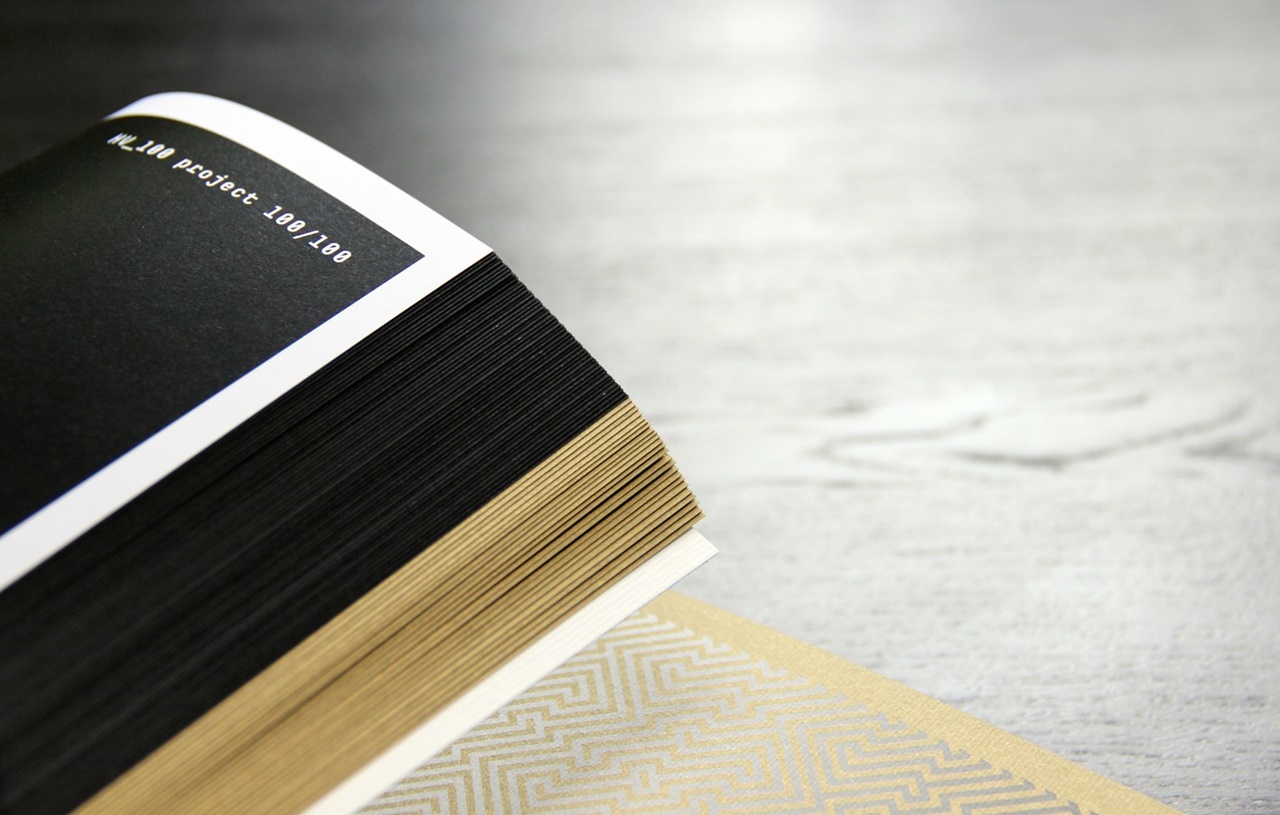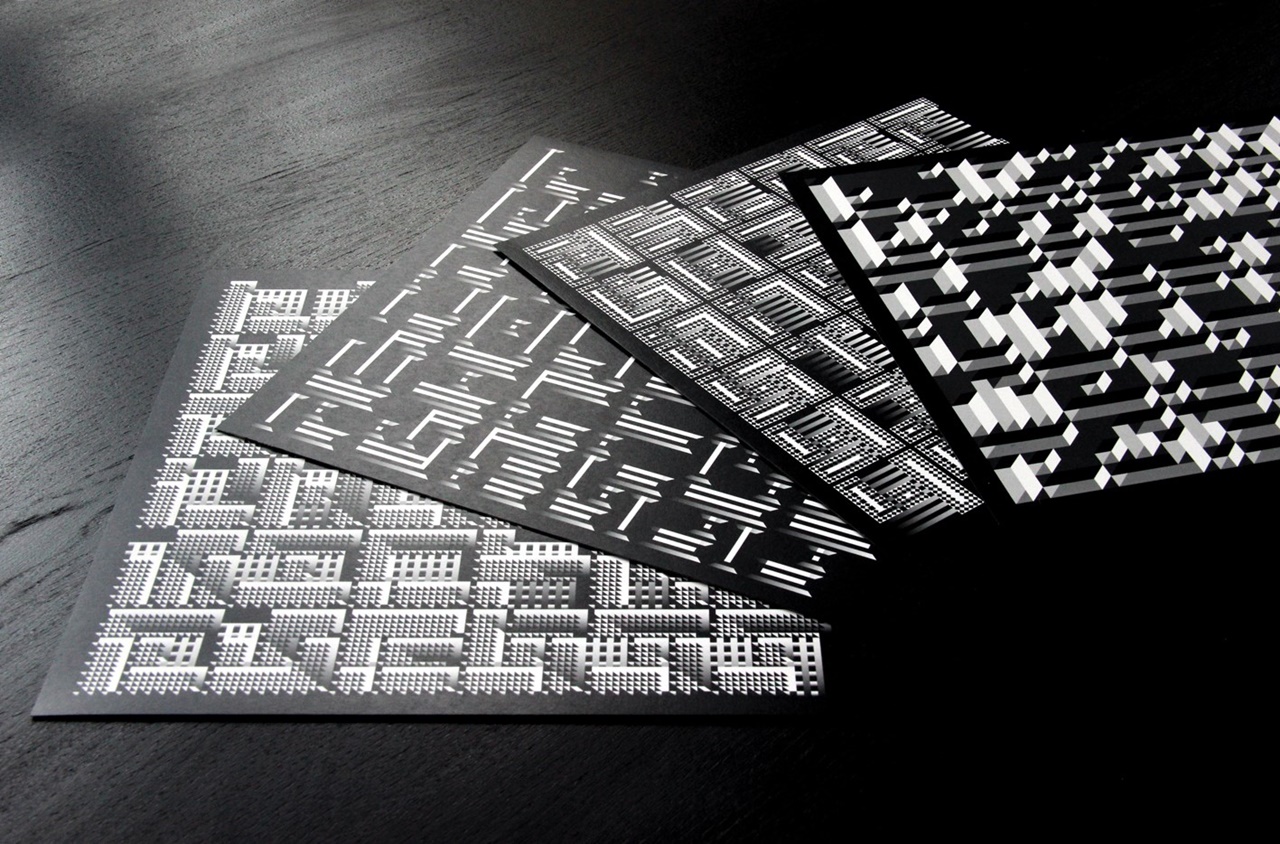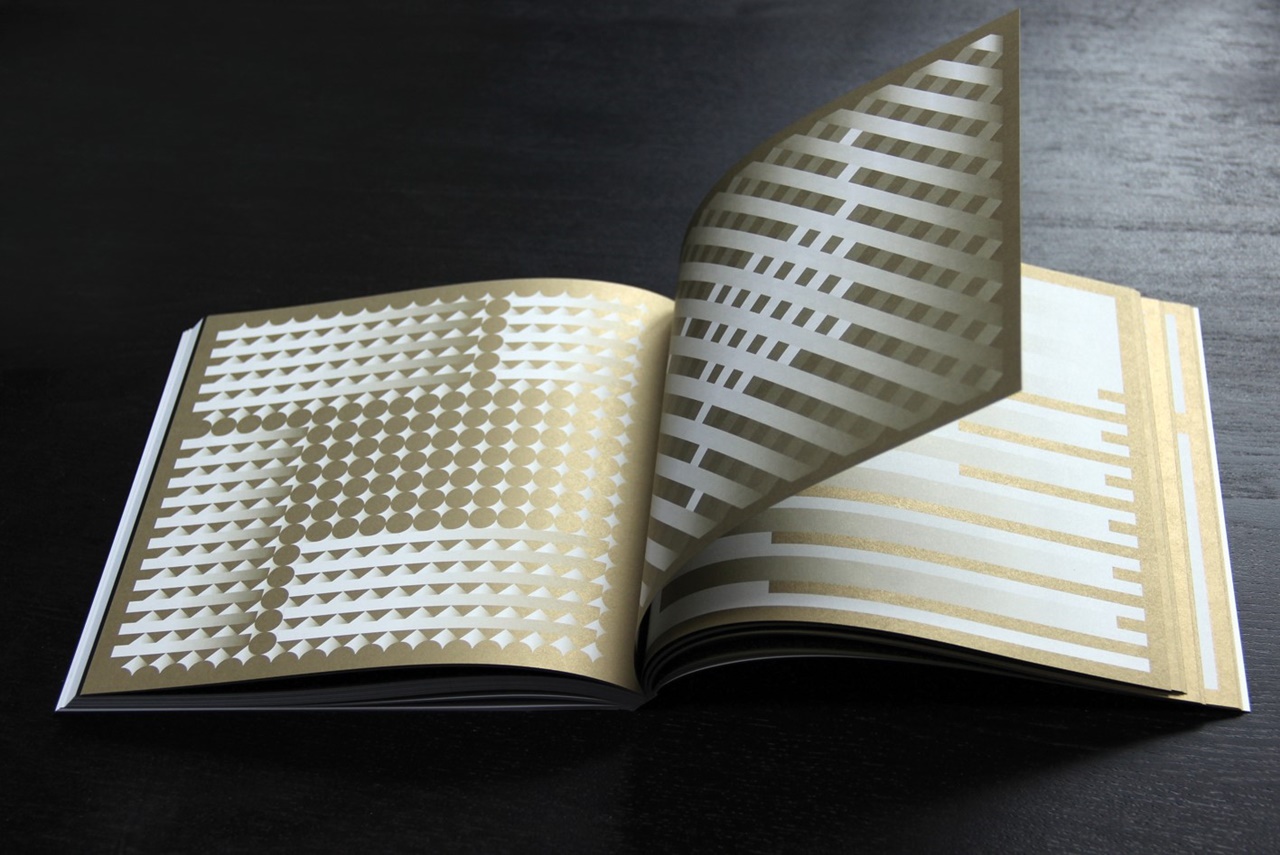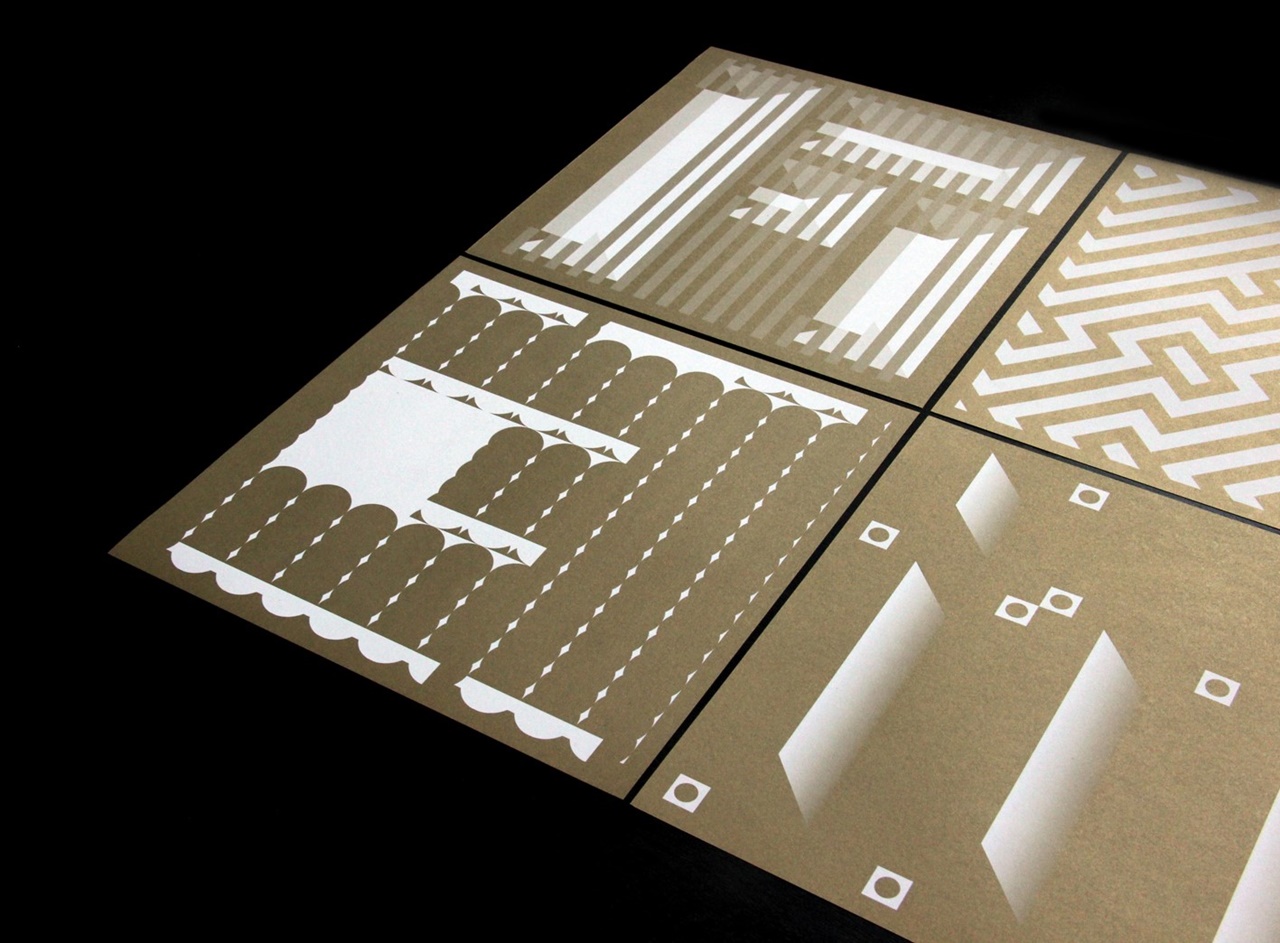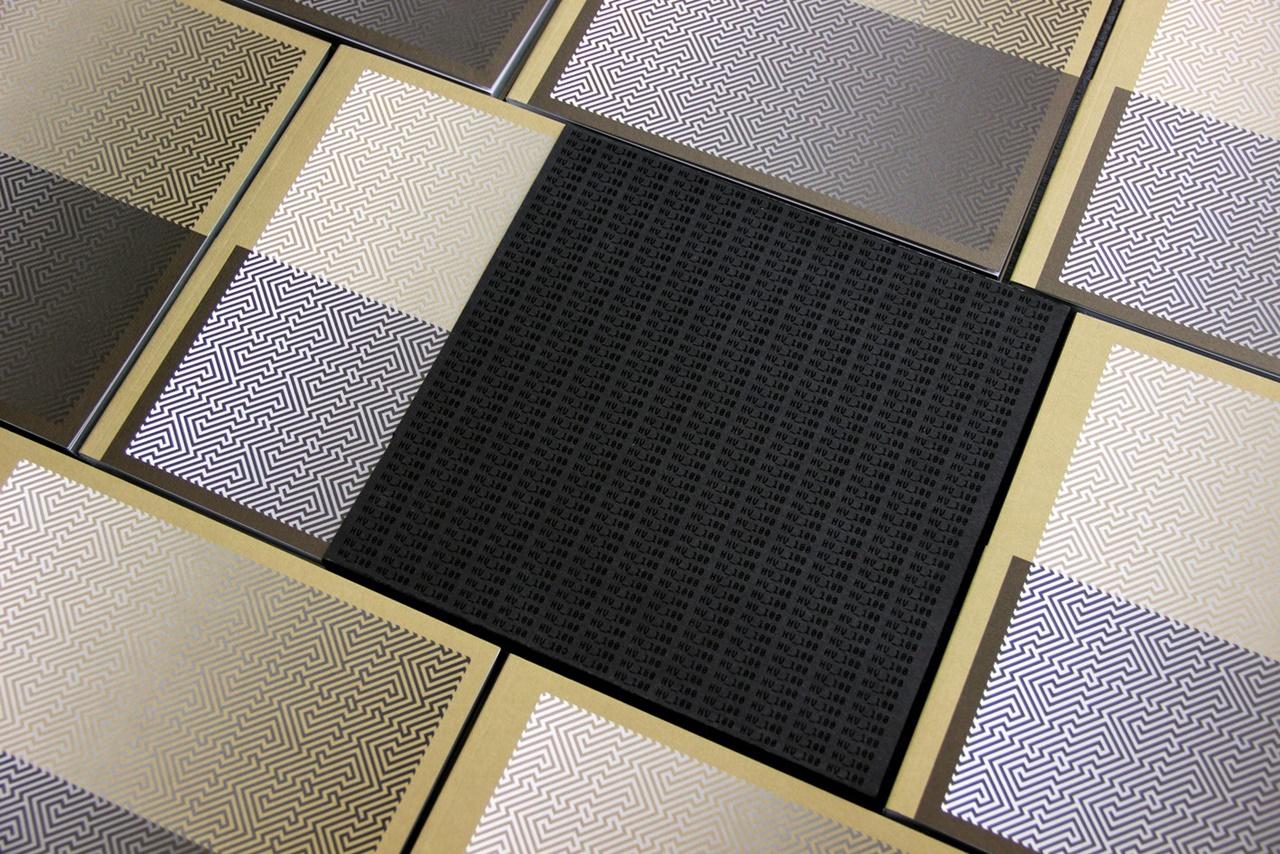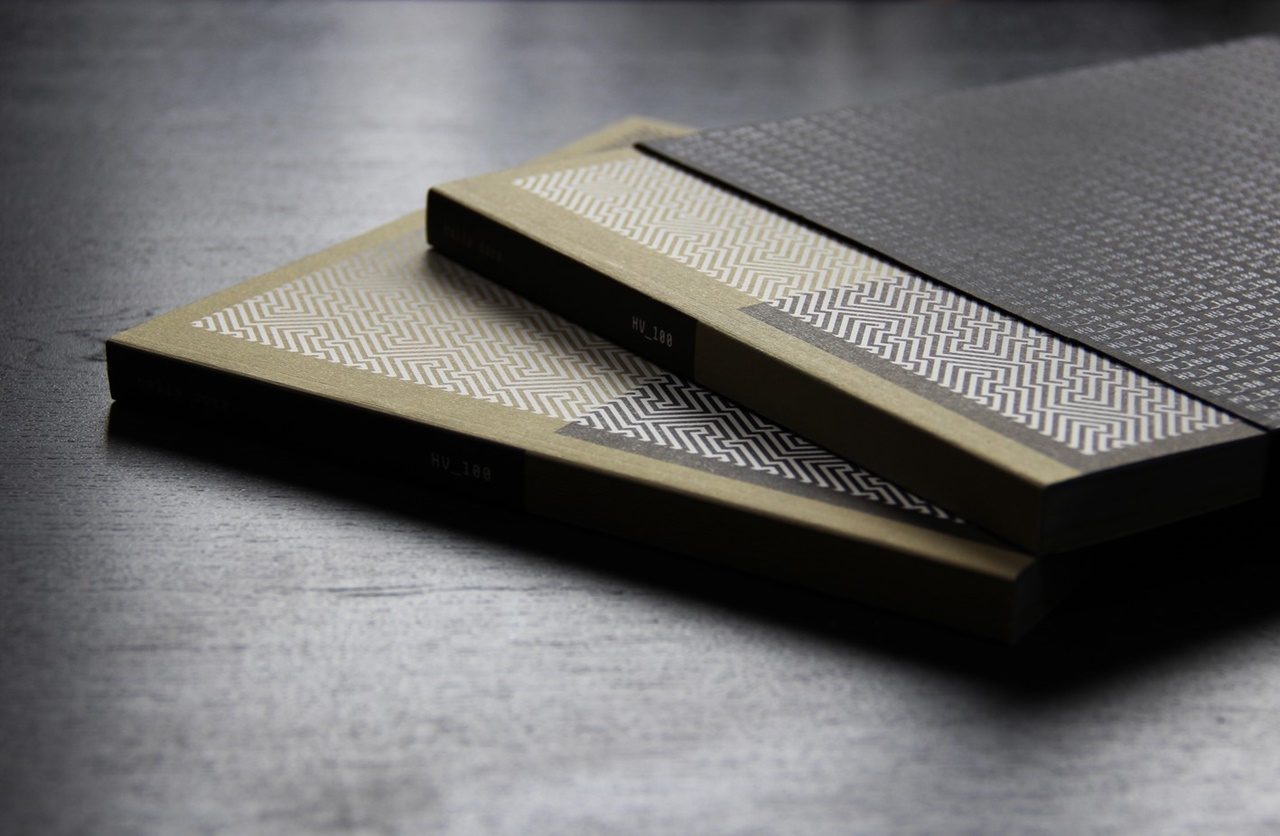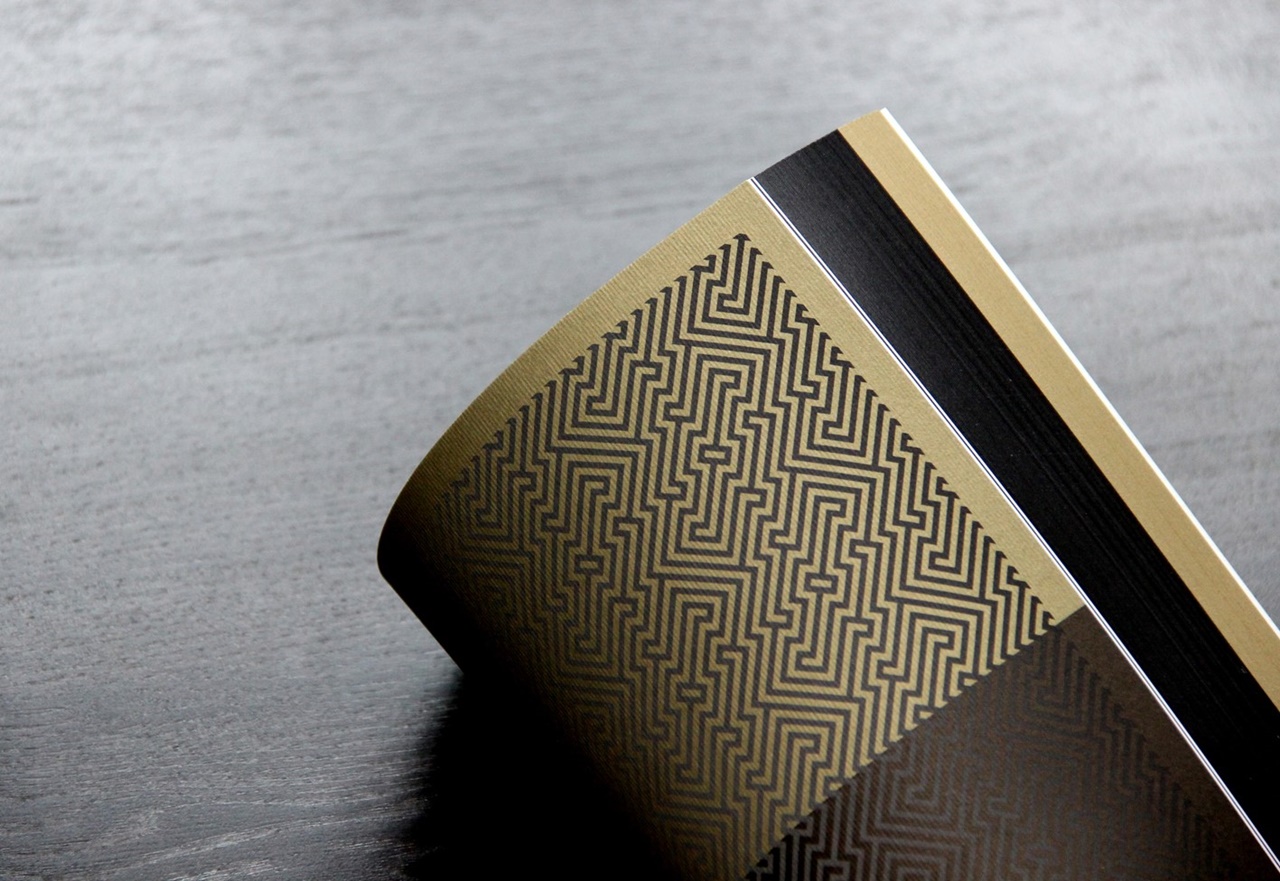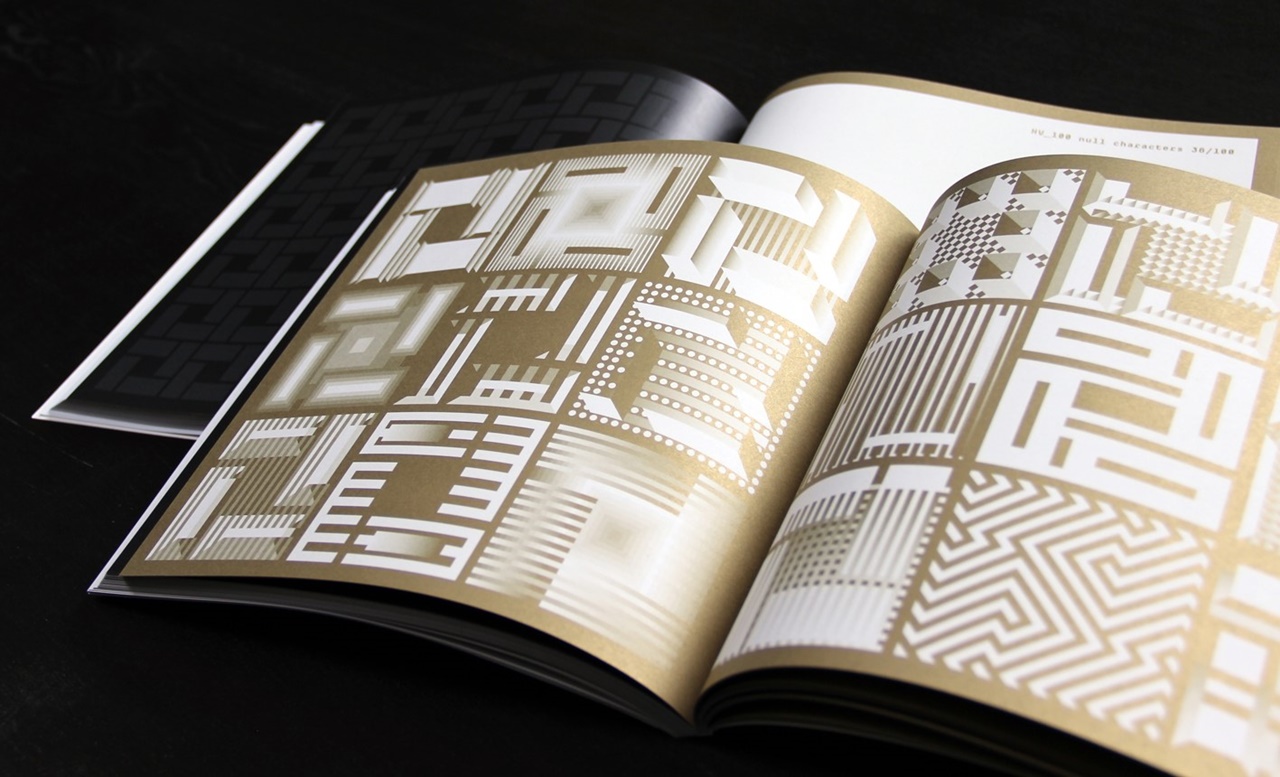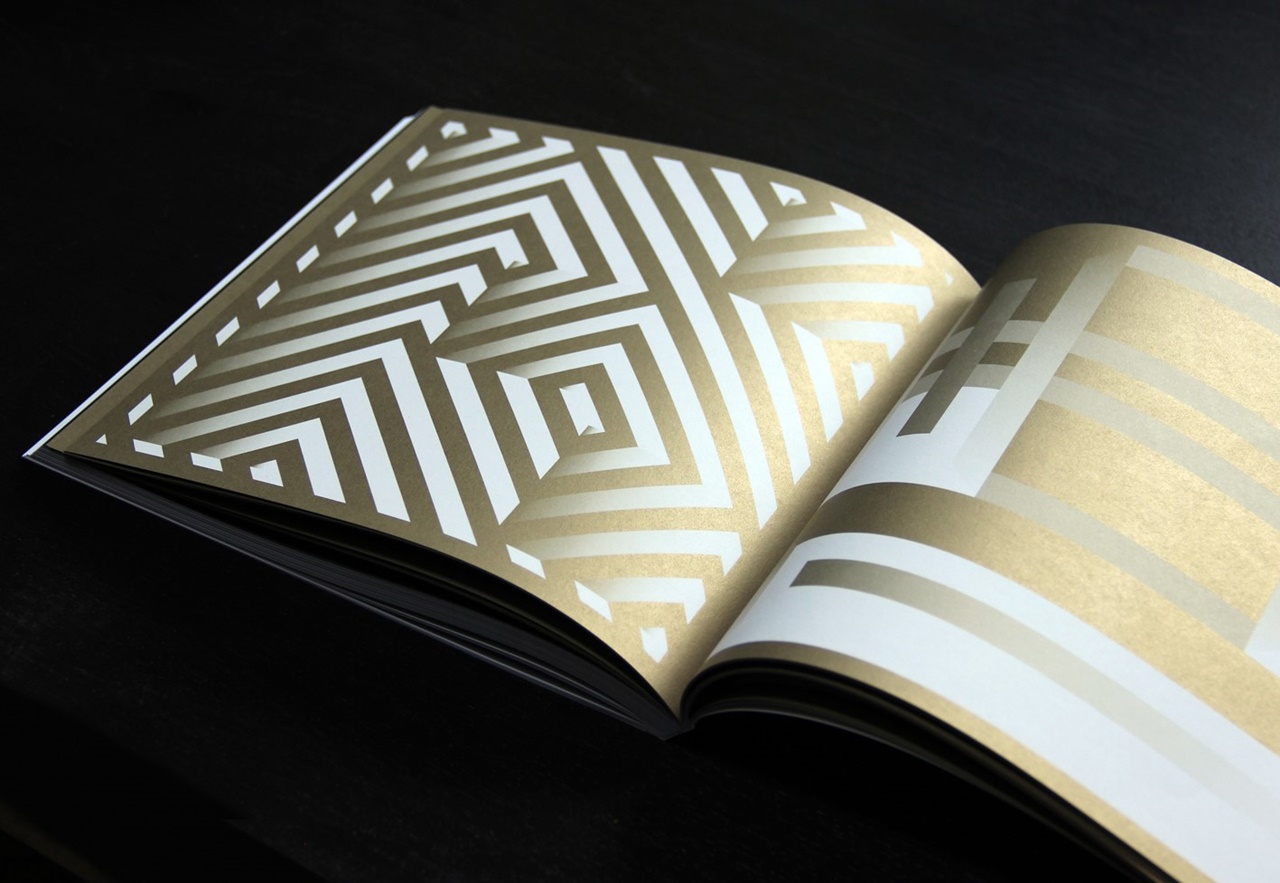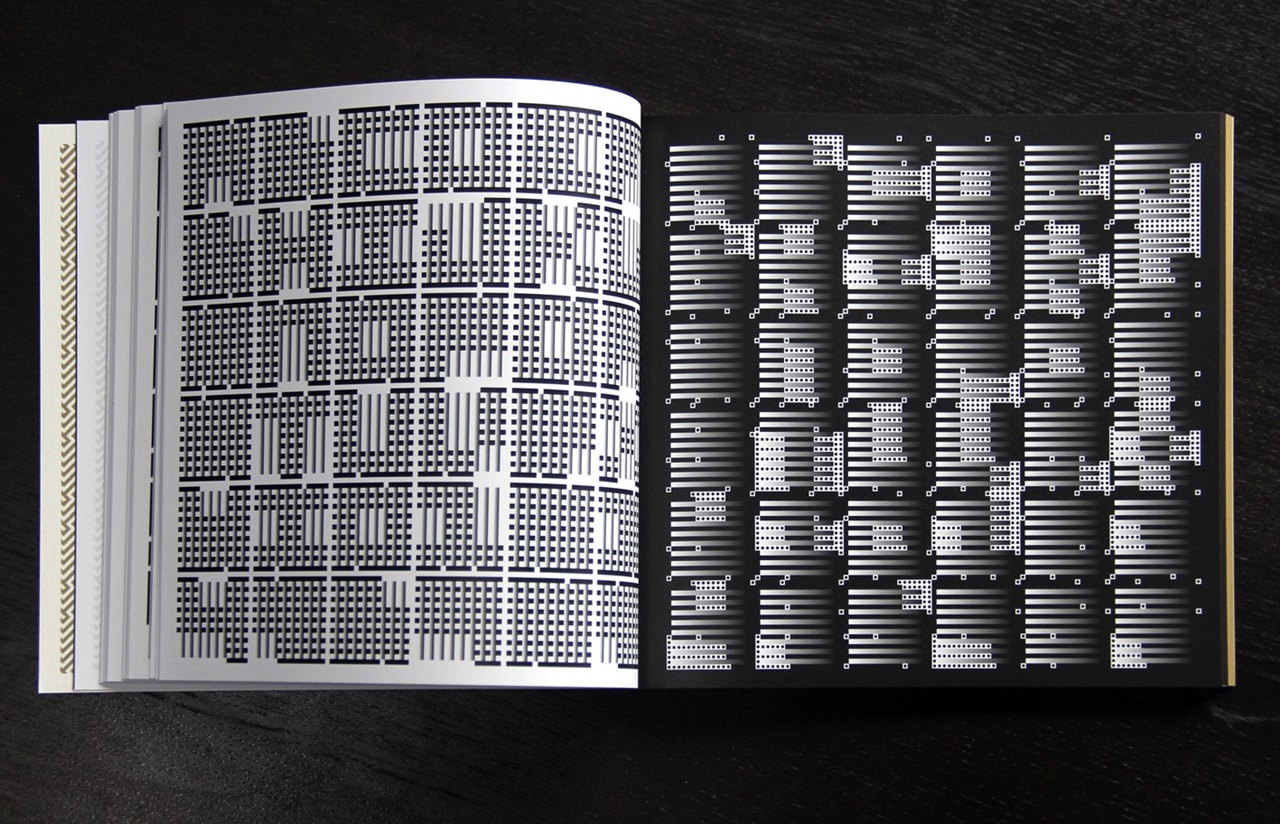
Kísérleti tipográfia 144 oldalon – Belenéztünk Balla Dóra legújabb könyvébe
Bevett szokás az alkalmazott, piaci grafika és az autonóm, művészi jellegű grafika teljes szétválasztása. Mintha a kettő között egy közmegegyezésen alapuló, aligha bolygatható összeférhetetlenség lenne. Balla Dóra mind a két oldalt magáénak tudhatja. Éveken keresztül dolgozott a kereskedelmi grafikában, mostanában pedig független, egyéni művei dominálnak. Munkáiban és az oktatásban is arra törekszik, hogy felhívja a figyelmet e két elszeparált kategória közötti átjárhatóságra.
Dóra tizenkét éve kezdett el tanítani, jelenleg is a MOME Tervezőgrafika Tanszékének oktatója. Szakterülete a kortárs szaktörténet, amelyről hamar kiderült, hogy nincsen magyar irodalma, de még a nemzetközi színtéren is hiányosságokat mutat. A hiánypótlás szándéka egy misszióvá nőtte ki magát, Dóra oktatási célból kezdett el blogot írni, amely kapcsán például a francia Étapes: szakbloggerként említi. Igazi digitális műgyűjtő, minden grafikával és vizuális művészetekkel foglalkozó embernek csak ajánlani tudjuk Balla Dóra digitális képtárát.
A Vizuális kutatás projekt is a történeti lemaradás felismeréséből indult el. Már az elnevezés is egy új szemléletről árulkodik, nem korlátozza magát a grafika és tervezőgrafika területeire, hanem ezeken túlmutatva, a vizuális kommunikáció és kultúra szélesebb spektrumai felé nyit.
A projekt egyik fontos célja olyan magyar származású személyiségekre felhívni a figyelmet, akik nemcsak alkotó, hanem teoretikus munkásságukkal is útmutatóként szolgálhatnak a jelen korban – aktualitásuk van. Így születtek meg a Kepes György és Moholy-Nagy László módszertanait kiindulópontként felhasználó és arra reflektáló korábbi kiadványok. „Egy magyar habitust lehet felfedezni munkáikban. Annak ellenére, hogy konstruktivista alkotásaik vannak, egy érzelmi réteg is rárakódik műveikre, ami sajátos hangot eredményez. Mindez egy más dimenzió felé nyitja ki a személytelen, analitikus művészetet.” – mondja Dóra.
A kiadványsorozat nemrég megjelent, harmadik részének Huszár Vilmos De Stijl logója az inspirációs forrása, amely köré egy tipográfiai kísérletezést épített ki Balla Dóra. A logó stencil modulrendszerű, tehát külön elemekből áll, ez szolgált alapjául a több száz betűtípusnak, amelyet Dóra kidolgozott. Egy évig készült a gridrendszer, és újabb egy évig tartott a karakterek kialakítása, a könyv tehát egy mélyreható experimentális munka végeredménye.
A De Stijl mozgalom századik évfordulójának alkalmából született meg a kiadvány. A számmal való játék többszörösen is megmutatkozik. A könyv első szász fekete-fehér oldalán a legizgalmasabb tipográfiai megoldásokat felvonultató variációkat láthatjuk, amelyet 500 betűkísérletből szelektált Dóra. Ezt követően kigyűjtve szemlélhetjük a nullás karaktereket. Ekkor a könyv arany színűre vált, visszautalva a centenáriumra, és 36 nullás karaktert mutat be, majd újabb 36 különböző abc karaktert (26 betű és 10 szám), demonstrálva ezzel a tervezett betűsorozat színességét és változatosságát. Ezt a kompakt tartalmat, puha kötésű, színesebb, és taktilis élményeket nyújtó fedőlappal ellensúlyozza.
Míg a Vizuális kutatás projekt korábbi kiadványainál hallgatók is közreműködtek, a HV_100 személyesebb vonatkozású, Dóra saját művészi nyomhagyása, ami saját egyéniségét tükrözi. A személyesség olyan finom gesztusokon érhető tetten, mint a null karakter d betűre való cseréje. A könyv továbbviteleként tekinthetünk Dóra legújabb munkájára, amely a null_style címet kapta. A Vizuális kutatás még korántsem ért végéhez, Dóra tele van ötletekkel, a projekt része a jelenleg futó Visual grammar tanfolyam is, amely ennek a gondolkodásmódnak a kiterjesztett kísérlete.